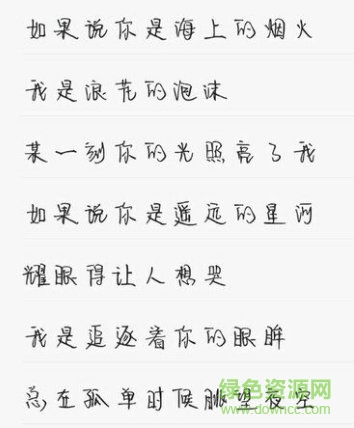
两小无猜字体是丁丁系列字体的特色手写字体,有着纯净而柔和的笔触,给人朦胧的现世安然感,字体行间跳动的都是倾心的喜悦,让人印象深刻,来绿色资源网下载即可使用!
两小无猜加粗版、两小无猜改小版都是在原字体上的处理而来,使用常规的加粗设置可以让文字变得硕大,给人更加清晰的视觉体验,可以运用在广告创意、艺术设计等领域!
丁丁两小无猜体